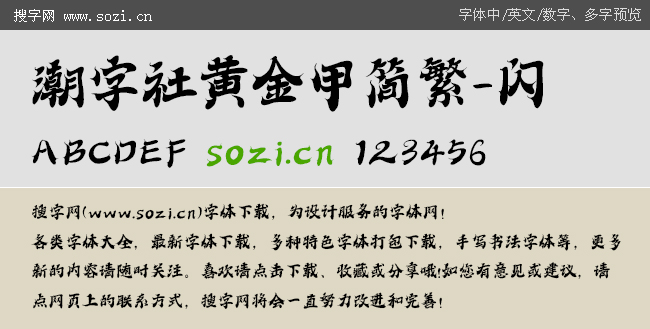
潮字社黃金甲簡繁-閃
搜字網(wǎng)提供一款潮字社黃金甲簡繁-閃中文字體下載,潮字社黃金甲簡繁-閃是一款非常獨特的個性毛筆藝術(shù)字體,這款字體總體結(jié)構(gòu)較為方正,在楷書的基礎(chǔ)上稍加隸書的圓潤、舒展之氣。筆畫入勢鋒芒盡顯,增加了字體的靈動性。字形撇捺開張,線條對比強烈,時而纖巧,時而厚重,波折起伏,巧于變化。運筆俯仰呼應(yīng),各有所據(jù)。字體擒縱自如,深具唐楷之意和古隸之美。適合應(yīng)用于藝術(shù)設(shè)計、平面宣傳設(shè)計、網(wǎng)頁設(shè)計等領(lǐng)域等應(yīng)用。(本字體為個人非商用版,商用請聯(lián)系作者購買授權(quán)。官方網(wǎng)址:http://www.reeji.com 聯(lián)系方式:021-58597892)